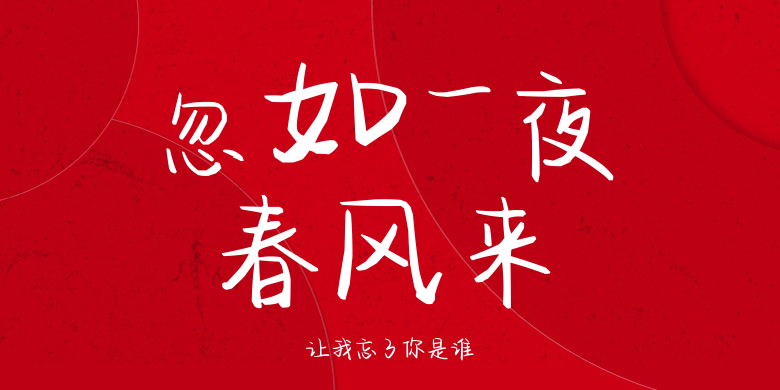
让我忘了你是谁
让我忘了你是谁,这款字体结构工整、笔画清晰,兼顾美观与易读性,适用于标题、正文、海报、包装、LOGO 等多种场景。字形优雅稳定,风格百搭耐看,适配日常排版与创意设计,让文字呈现更舒适、更具质感。让我忘了你是谁一笔一画,皆是细节,以均衡的比例、流畅的线条打造舒适视觉体验,字形端正大气,风格简约现代。无论是商业设计、品牌宣传还是日常排版,都能轻松驾驭,让文字更有格调与力量。让我忘了你是谁字体下载。